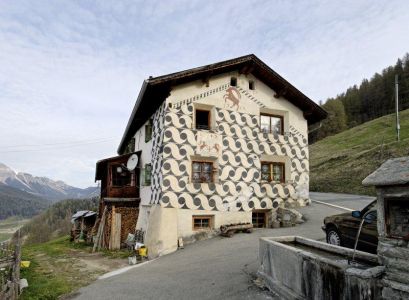
Da steht dir eine ganze Welt von Möglichkeiten zur Auswahl. Einige Hinweise auf die Schnelle:
Naheliegend wäre ein Urlaub hier in Graubünden, wo du in der wahren Nusstortenheimat – dem Unterengadin – lokale Buchdruckgeschichte bewundern kannst oder dir bei einem guten Glas Veltliner den speziellen Schriftenmix (TheMix/Syntax) der Marke "graubünden" zu Gemüte führst. Oder im gleichen Tal wirklich alte "Graffitis" studierst (die gibts auch in manch anderen unserer gut und gerne 1000 Täler).
(Haus Padrun, Andeer, oberhalb der Viamala-Schlucht an der San Bernardino-Route)
Du kannst aber auch diesen ganzen Thread aufmerksam durchlesen und irgendwo einen typografischen Schatz heben und ihn digitalisieren. Oder einfach warten, warten. Die Hoffnung stirbt ja bekanntlich zuletzt ... ;-)
hast du ein größeres bild von dem haus? das sieht ja fantastisch aus. :o
Bitte, gern geschehen – ein größeres Bild vom Haus Padrun kann ich dir nur mit einem weiterem Link bieten.
Ich muss mich trotz allgemeinen Stresses und sehr eingeschränktem Internet-Zugang* zur Nusstorte äußern: Ganz ganz köstlich, das haben alle bestätigt denen ich (ungern) ein Stück abgegeben habe!
* es ist kaum zu glauben wie lange die Einrichtung eines Internetzugangs dauern kann im 21. Jahrhundert...
Ein richtig abgefahrenes Sgraffito-Haus ist auch dieses aus dem 16. (!!) Jahrhundert,
das in der höchstgelegenen Gemeinde der Schweiz steht:
Der Ort trägt übrigens den schönen Namen: Lü (sic!).
in der höchstgelegenen Gemeinde der Schweiz steht
Da man ja hier herum gar trefflich bis ins Detail streiten mag: Lü im Val Müstair ist auf 1920 m ü. M. die höchste POLITISCHE Gemeinde der Schweiz. Juf im Averser Tal hingegen ist das höchste ganzjährig bewohnte Dorf Europas auf (noch?) baumlosen 2126 m ü. M.
So, nach endlosem Umzugszeug konnte ich mich wieder mal einen Abend in Ruhe hinsetzen.
Neu in Version 0.6:
- Nochmal schmalere A, V, W
- mehr Feinabstimmungen, weniger Rastertreue – aber kein Aufgeben des Rasters
- Kerning Kerning: Satzzeichen, Leerzeichen, vergessene Buchstabenkombinationen
- überarbeitete Diakritika – weg von Tschichold, hin zu mehr Homogenität
Bis auf wenige Details (Anführungszeichen, Beistrich) würde ich sagen sie ist fertig. Was meint ihr?
ach ja: hier ist sie.
Wie sieht’s mit Ligaturen aus? Gerade weil das f recht breite Waagerechte hat, sieht z. B. »Profi« ohne Ligatur gewöhnungsbedürftig aus. Schön, daß es ein Lang-s gibt, hier scheint mir aber auch die waagerechte Dimension ziemlich raumgreifend.
JT clavella
JT = Jan Tschichold; "clavella" = (hölzerner) Nagel
JT reschniev
JT = Jan Tschichold; "reschniev" = nagelneu
(die romanischen Worte tönen dann gut, wenn ihr den 2. Vokal betont ;-) )
JT Nagelneu?
Mo ... johhh ... passt scho.
Norbert
FF Nusstorte?
Mais, alors, la bas! "FG Nusstorte", enfin, si jamais ...
:lol: